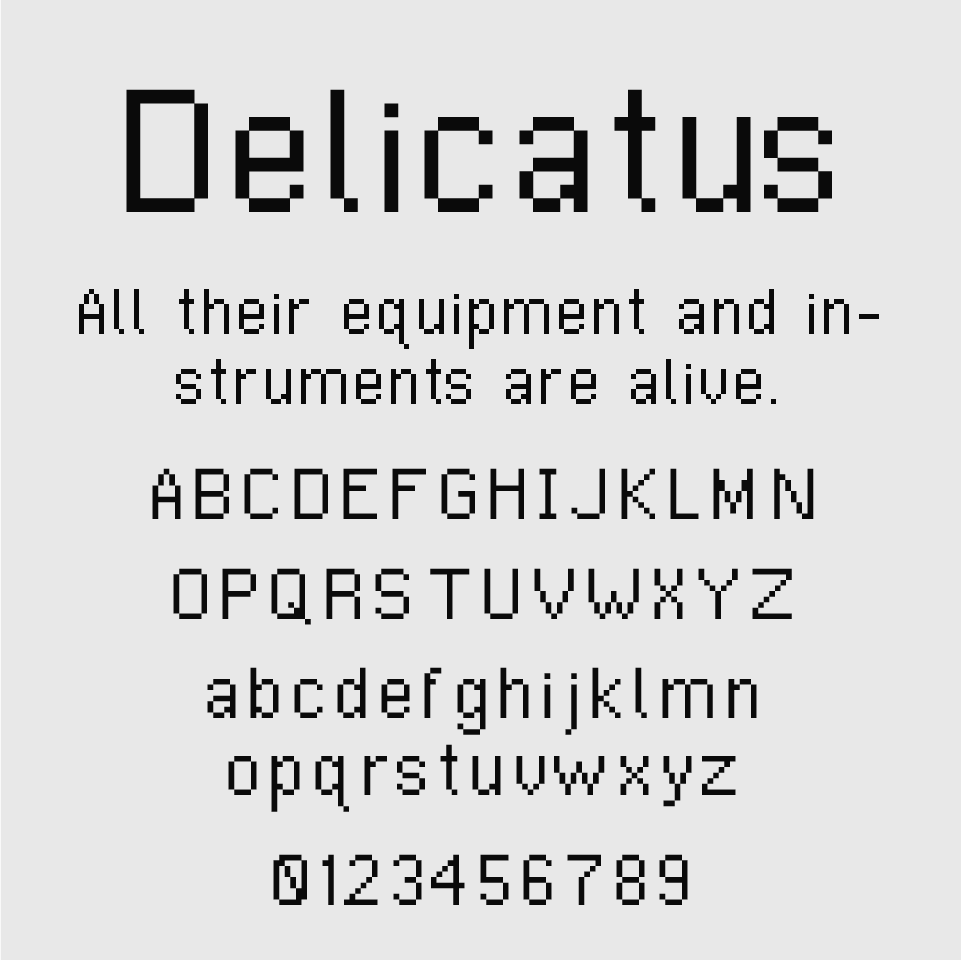
Delicatusフォントは、精緻さと繊細さが際立つピクセルフォントです。
ドット絵やファミコン時代のようなタイポグラフィを彷彿とさせるシンプルなピクセル文字でありながら、ちょっとスリムにも作られており、どこか清潔感がありスタイリッシュな印象も兼ね備えています。
カクカクとした線に可愛らしさがあり、レトロな表現だけでなく、テック系やアート系のデザインにも応用可能です。小型ディスプレイ風の表現やインターフェース演出にもぴったりです。